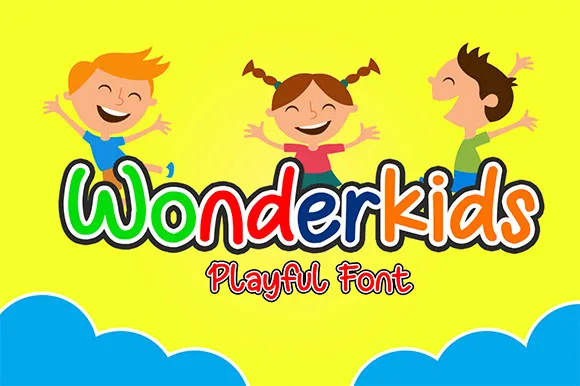
Wonderkids Display Font – Download Grátis
Esse é Wonderkids Display Font, uma nova adição à nossa gama de fontes. Com seu tema infantil divertido e cheio de vida, ele traz uma sensação amigável e descontraída a qualquer projeto gráfico. Ideal para personalizar logotipos ou designs em cartazes, Wonderkids é uma excelente escolha para quem procura algo que brinque com o visual sem deixar de lado a funcionalidade. Através da fonte Wonderkids, você pode criar projetos de design cheios de personalidade e encanto. Experimente essa nova opção e transforme seus trabalhos em verdadeiros stands singulares.